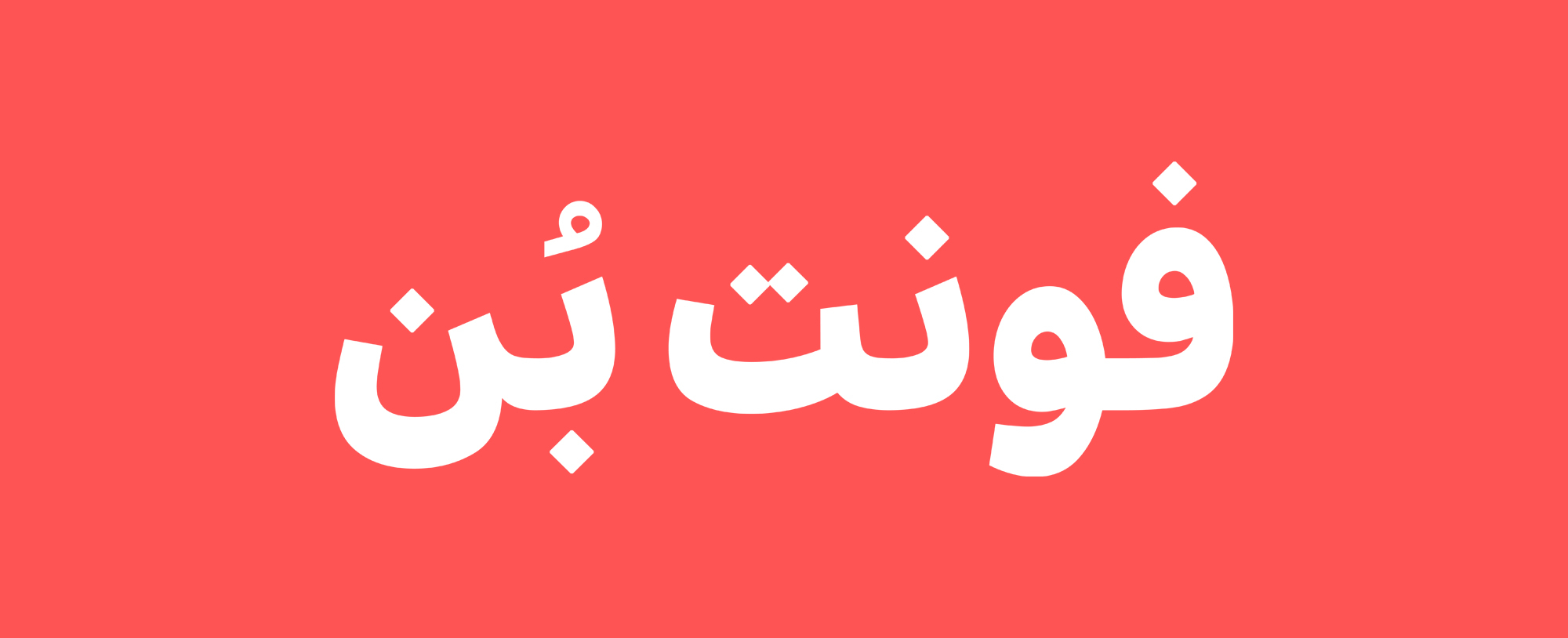
فونت بن
فونت بُن در واقع یک خانواده فونت با ۱۰ وزن است که برای پاسخ به نیازهای پایه و روزمره طراحی شده. هدف آن ارائه‌ی فونتی خوانا، تطبیق‌پذیر و همه‌کاره است که به‌راحتی در انواع فضاهای طراحی – از رابط‌های کاربری تا متون چاپی – استفاده شود.
فونت بُن خوانایی را در اولویت قرار داده و از هرگونه تزئینات پرهیز می‌کند. این فونت با سادگی و حضور کم‌رنگ خود، به محتوا اجازه می‌دهد تا در مرکز توجه قرار گیرد و به ابزاری ضروری در جعبه‌ابزار هر طراح تبدیل شود.
نام «بُن» که در فارسی به معنای "ریشه" و "بنیاد" است، بازتابی از نقش بنیادی این تایپ‌فیس در سیستم‌های تایپوگرافیک است. طراحی بُن از سال ۱۴۰۱ آغاز شده و به‌مرور زمان تکمیل شده است.
طراحی بُن با الهام از نسل تایپ‌فیس‌های کاربردی و روزمره که هویت بصری ما را شکل داده‌اند، طراحی شده، اما نقش خود را در دنیای مدرن بهینه‌سازی کرده است. این فونت ضمن پایبندی به ساختارهای سنتی حروف، بر خوانایی، تعادل و روانی فرم‌ها تأکید دارد.
تنوع وزن‌ها در فونت بُن
بُن یک خانواده‌ی تایپ‌فیس با ۱۰ وزن، از Hairline تا Black است که به طراحان امکان طیف گسترده‌ای از وزن‌های نوشتاری را می‌دهد. از نوشته‌های ظریف و سبک تا نوشته‌های قدرتمند و تأثیرگذار.
نام این فونت از واژه‌ی فارسی "بُن" گرفته شده که به معنای ریشه، پایه و اساس است—تعریفی که کاملاً با ماهیت آن همخوانی دارد. بُن به عنوان یک ابزار پایه در سیستم‌های تایپوگرافی طراحی شده است و خوانایی، تطبیق‌پذیری و عملکرد بی‌دردسر را بر تزئینات بصری ترجیح می‌دهد. این فونت بدون جلب توجه غیرضروری، به‌راحتی در انواع فضاهای طراحی ادغام می‌شود.
بُن تلاش نمی‌کند تا خودنمایی کند؛ بلکه محتوا را در اولویت قرار می‌دهد. این فونت برای همراهی، نه سلطه‌گری طراحی شده است و تجربه‌ای روان و بدون اختلال در خواندن را فراهم می‌کند. حضور آن در جعبه ابزار یک طراح نه‌تنها مفید، بلکه ضروری است و امکان استفاده در فضاهای متنوع چاپی و دیجیتال را فراهم می‌کند